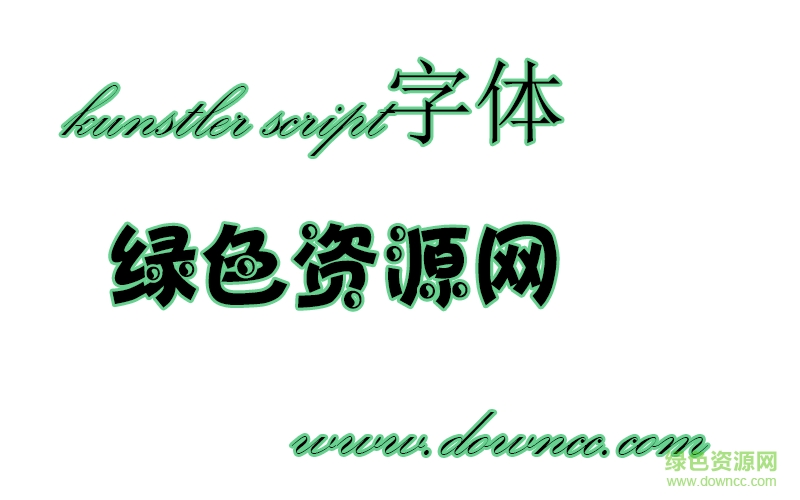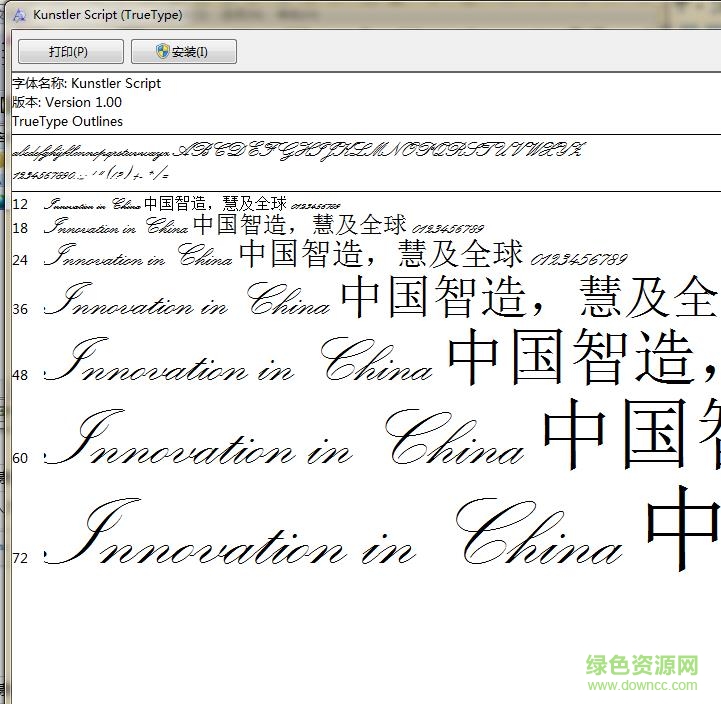
kunstler script字體非??蓯?,十分的細(xì)膩,較之狂草更為開放,讓你完全認(rèn)不出英文字體的樣式,但是在眾多的藝術(shù)字表現(xiàn)形式上依舊十分受歡迎,帶給你一種藝術(shù)的美感!
這款字體給我的感受是在字母開頭都擁有十分巨大的扭曲效果,讓你能一眼看每個單詞都看到首個單詞,十分顯眼,同時也帶給你不錯的視覺效果!